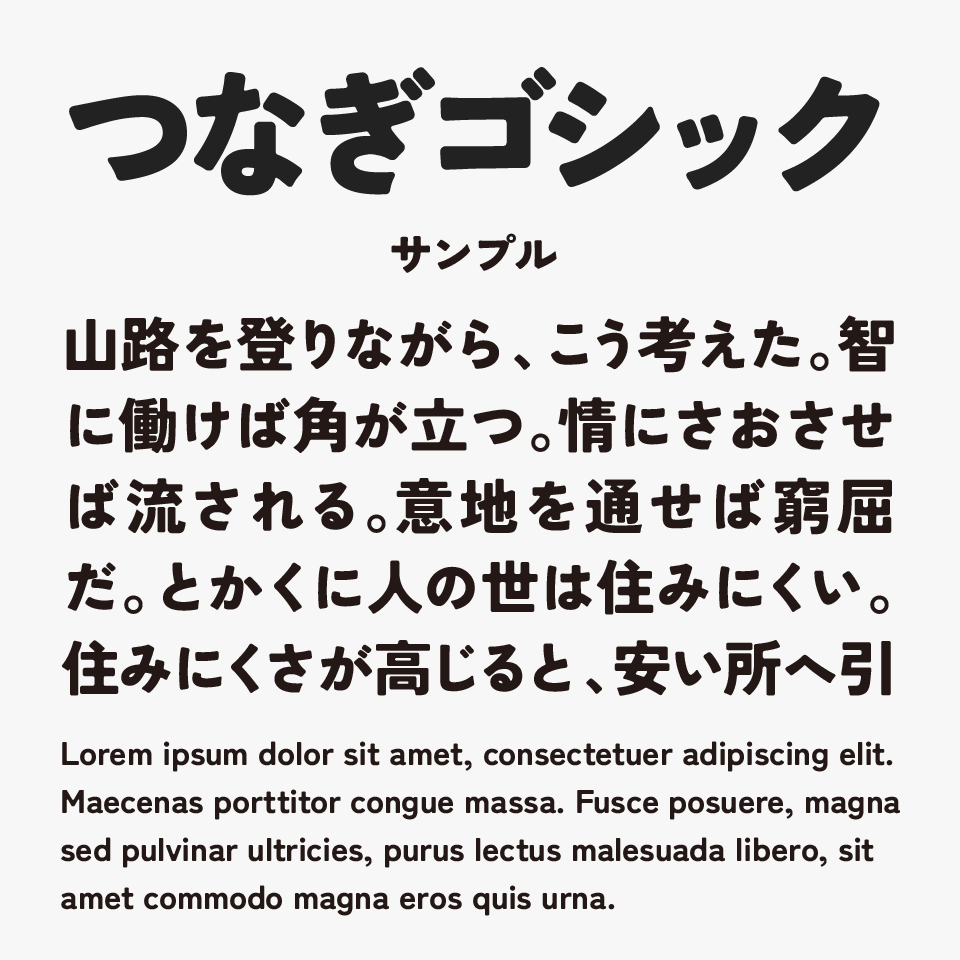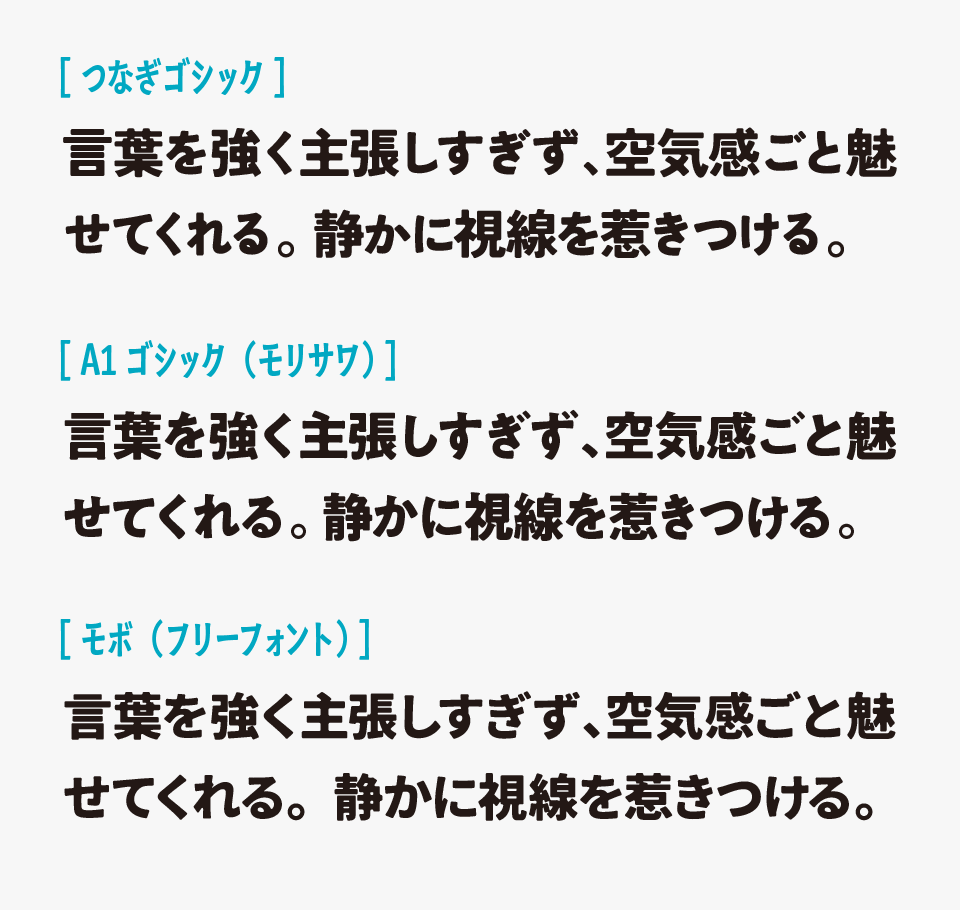
つなぎゴシックは、オープンソースフォントである「Zen角ゴシックN」をベースに、角を丸く加工し、墨だまり処理を加えたフォントです。
太いゴシックでありながら、角丸加工が柔らかな印象をあたえ、こぶりなひらがな・カタカナのデザインも柔らかく優しい雰囲気をもたせているフォントになっています。
太めのゴシックなどので、タイトルやキャッチコピーでももちろん、動画のテロップや字幕などのシーンでも活躍できるフォントです。
太めのゴシック・角丸・墨田まり加工から、フォントメーカーモリサワの「A1ゴシック」に似ているフォントを探している方でも代用できるフォントではないでしょうか。
収録文字は、ひらがな・カタカナ・アルファベット・数字・漢字は教育漢字、常用漢字、第一水準漢字、第二水準漢字が含まれています。